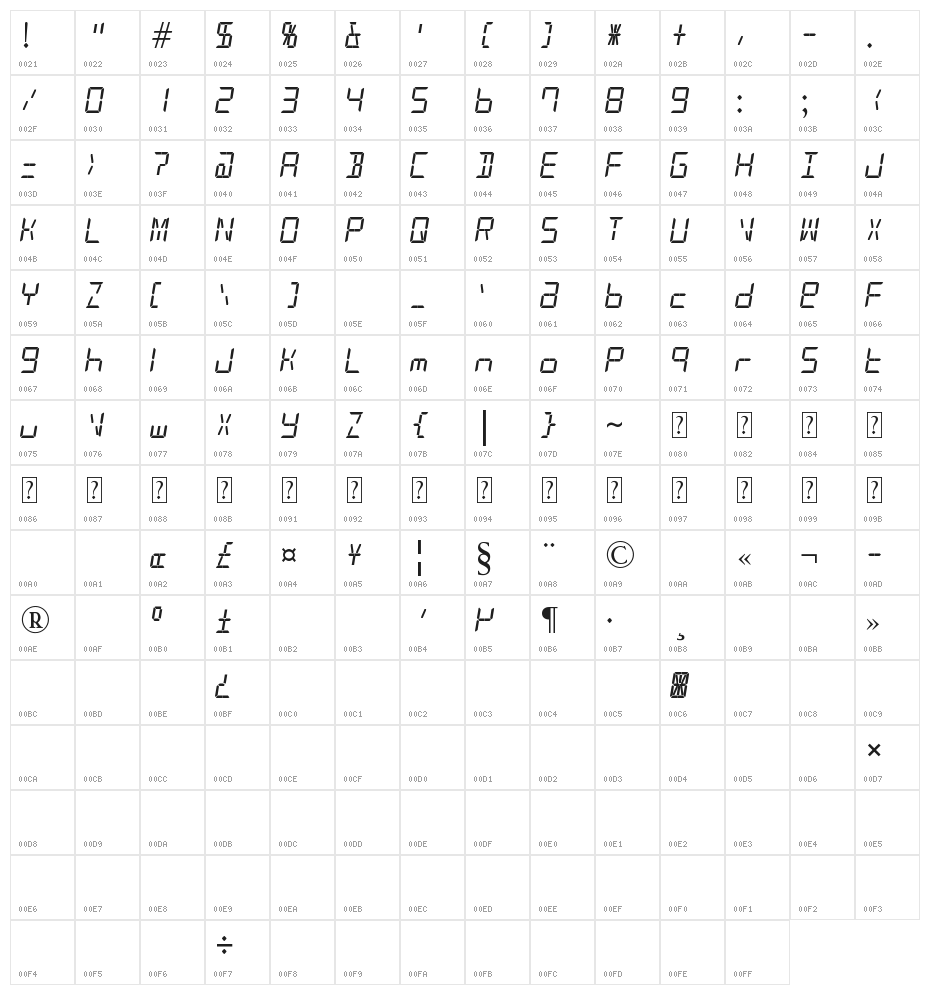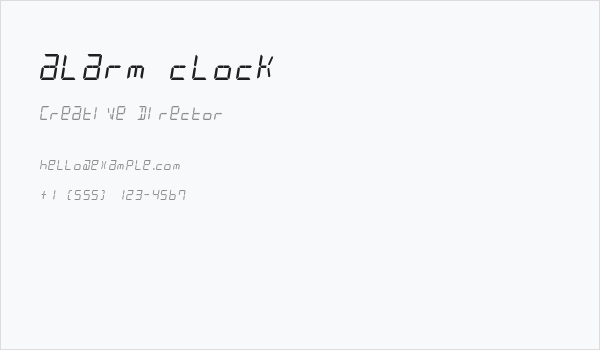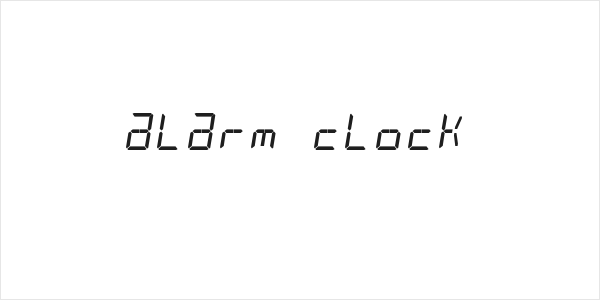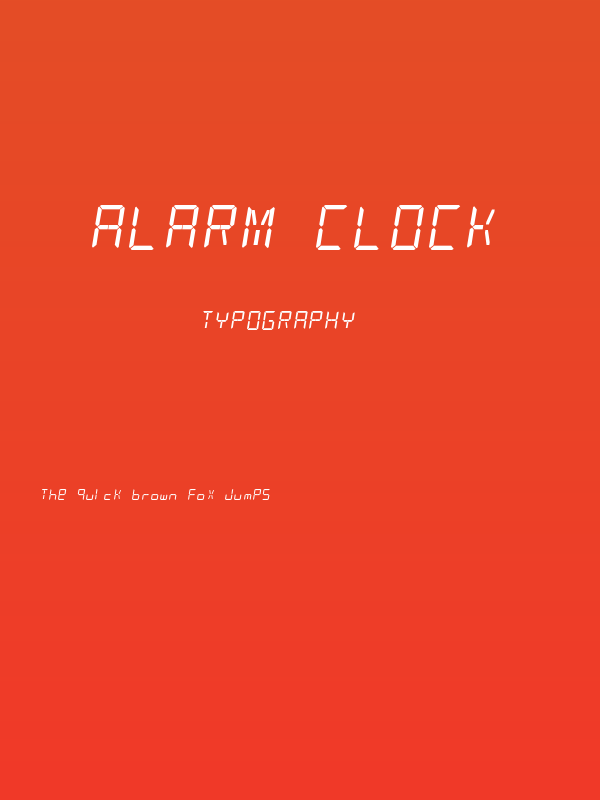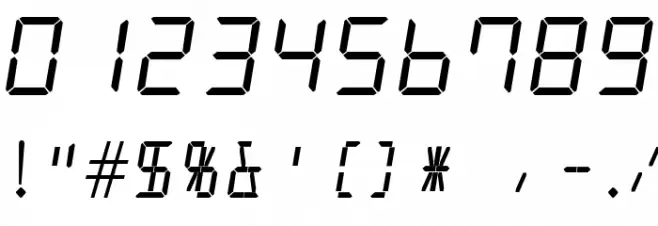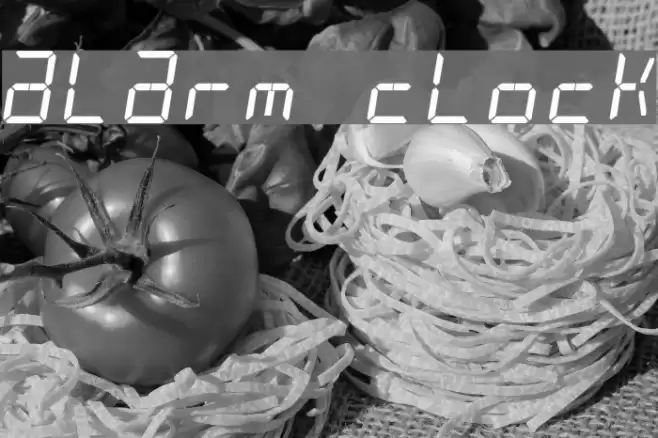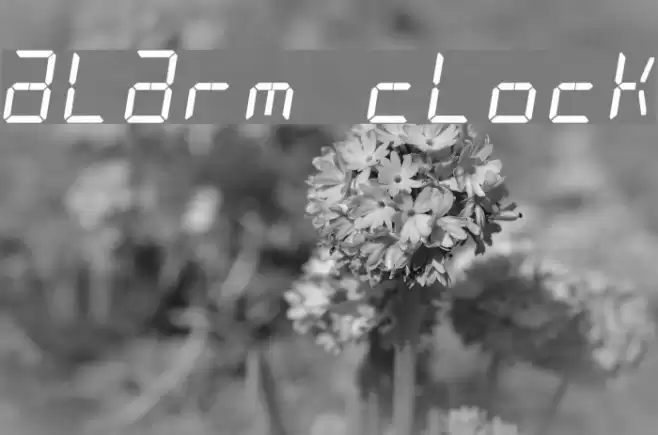
alarm clock Font
ALARM-CLOCK Groß
ALARM-CLOCK Kleinbuchstaben
ALARM-CLOCK Anderer Schreiben
| Vorgeschlagene Projekte | Perfect for digital clocks, tech-themed posters, electronic device interfaces, and futuristic branding. |